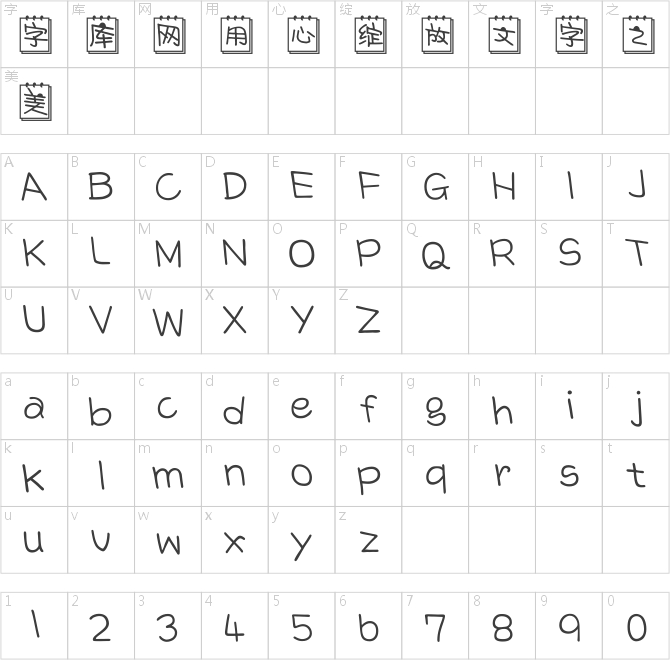
騰祥日歷體簡(jiǎn) 詳情頁
字體名稱: 騰祥日歷體簡(jiǎn)
騰祥日歷體簡(jiǎn)字體字庫是一款讓人賞心悅目、百看不厭的中文字體,適合各類廣告和產(chǎn)品包裝設(shè)計(jì)應(yīng)用,字體大小5.98MB,格式為ttf字體,上傳用戶是多拉MO,作者/版權(quán)方為騰祥字庫